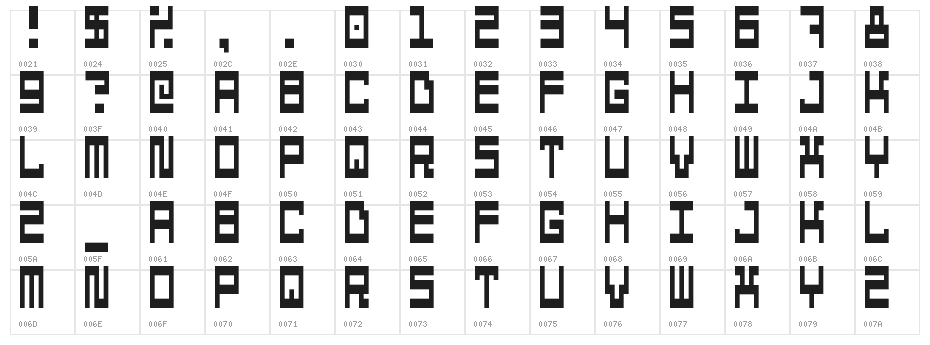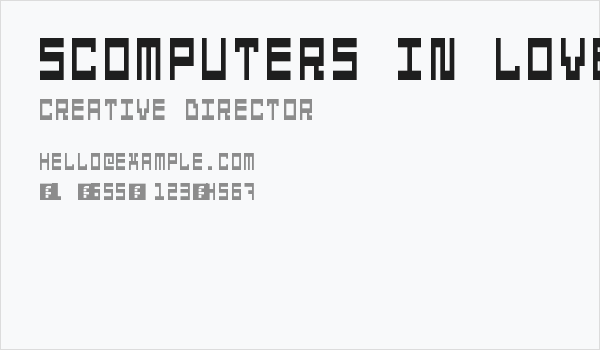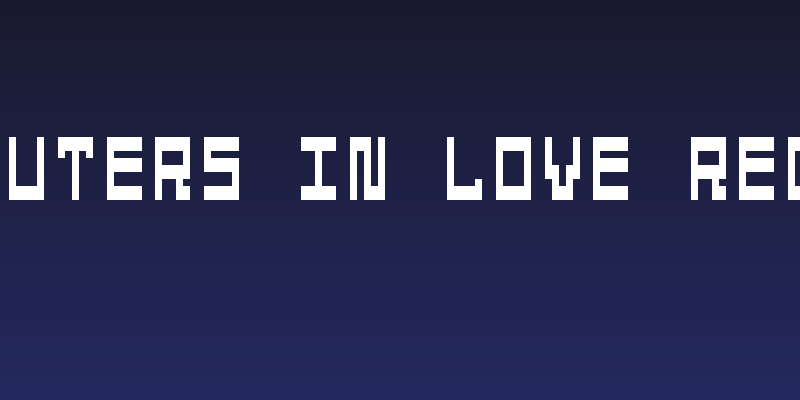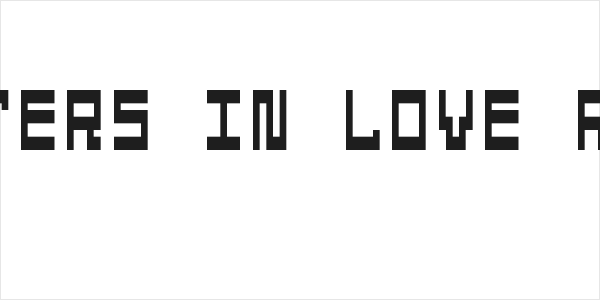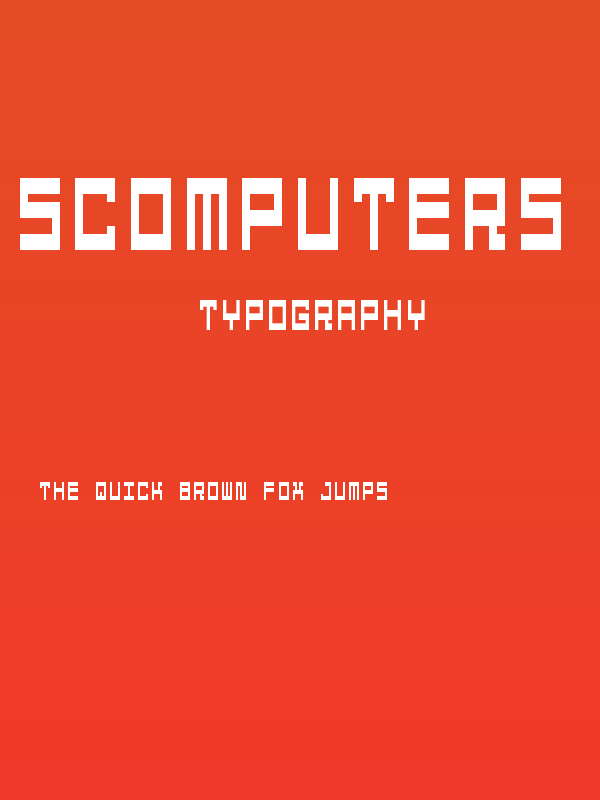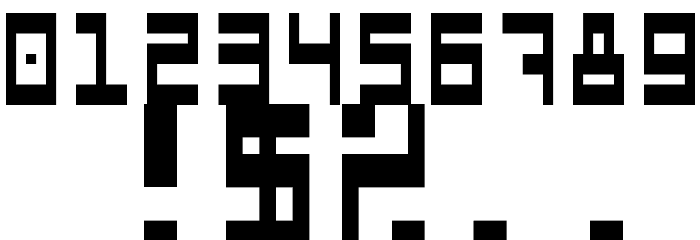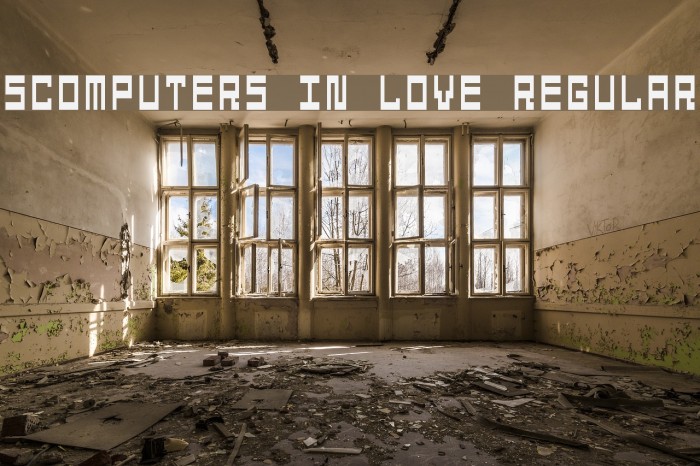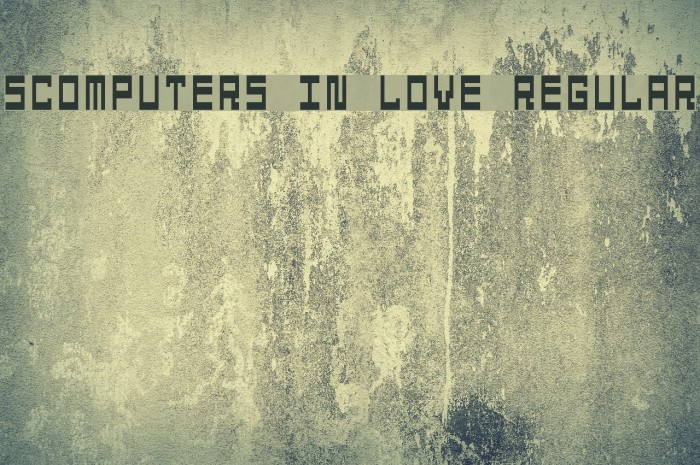
5Computers In Love Regular Font
| Рекомендуемые проекты | Ideal for tech-themed designs, video game graphics, digital art projects, and futuristic branding. |